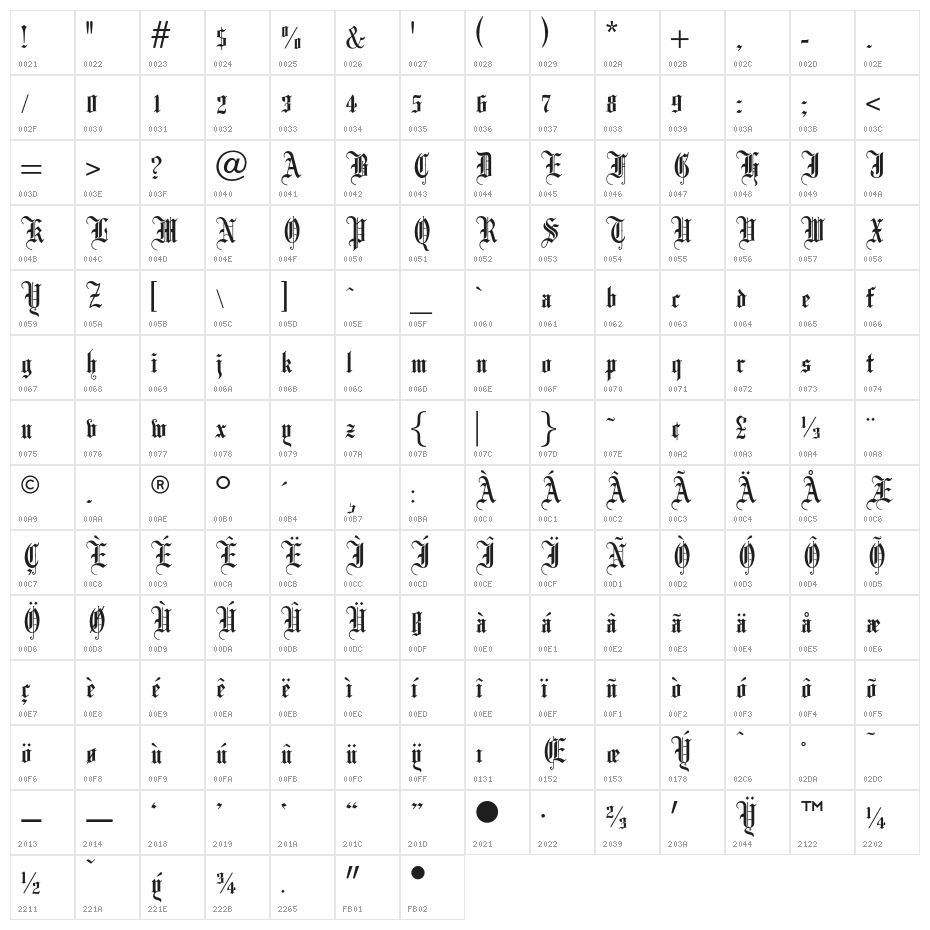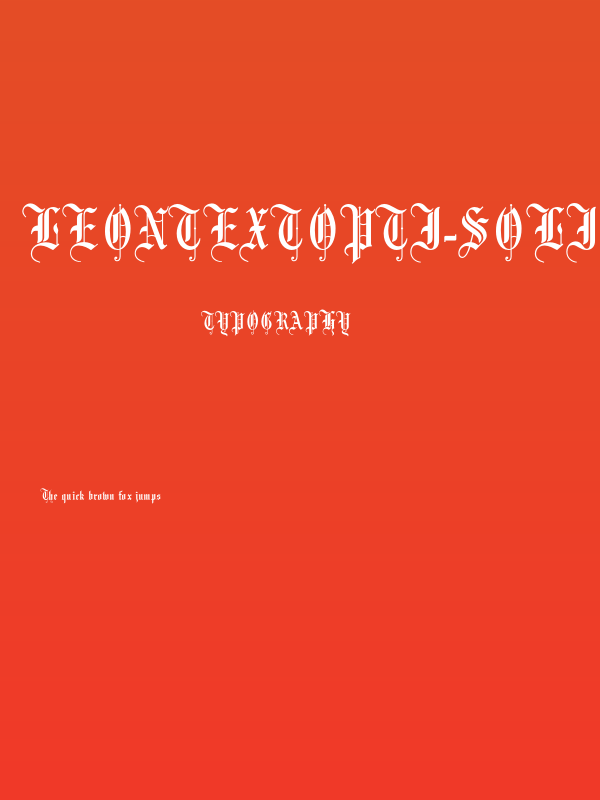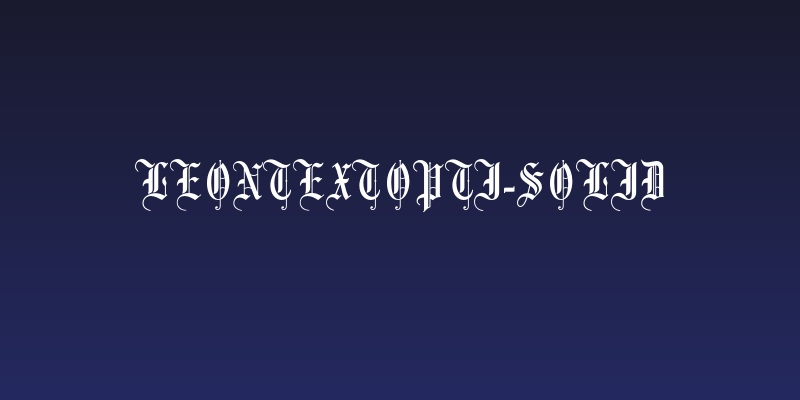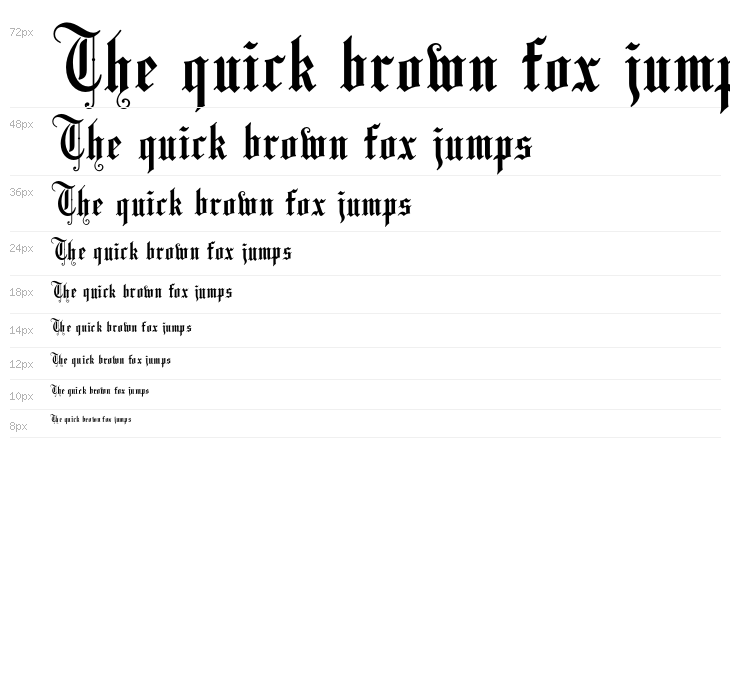
LeonTextOpti-Solid Font
✎ Gothic
| Caz de utilizare | Logos, Headlines, Decorative text |
| Proiecte propuse | Ideal for projects that require a vintage or medieval aesthetic, such as historical documents, event invitations, or branding for traditional products. |